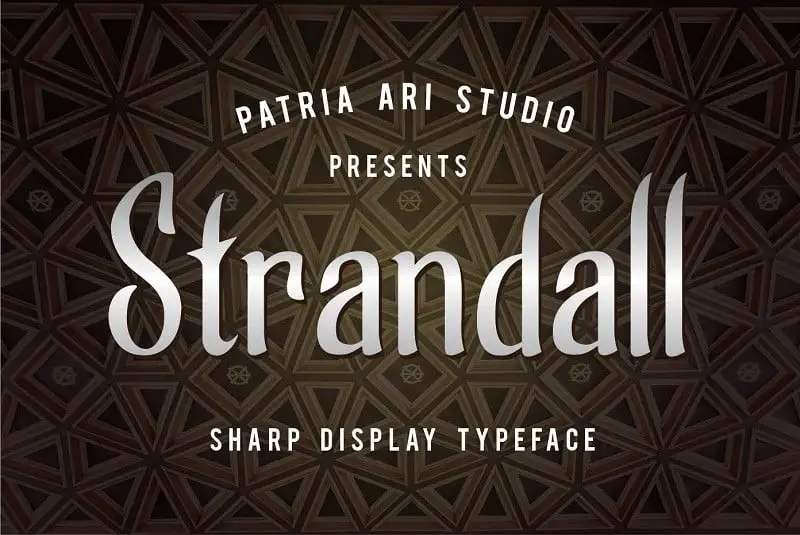
Strandall Display Font – Download Grátis
A “Strandall Display Font” é uma tipografia inspirada nas temáticas guerreiras, proposta para dar um toque poderoso aos seus projetos ou marcas. Com linhas aguçadas e linhas fortes, ela busca transmitir confiança e atrevimento. Este tipo de fonte foi criado com a intenção de reforçar sua marca ou projeto visual, adaptando-se perfeitamente para uso em logotipos, materiais de marketing ou qualquer outro material que precise de uma aparência imediata e poderosa. Seja você um estilista gráfico ou designer de identidade, esta fonte é a escolha ideal para criar elementos visuais impactantes e memoráveis. Inspirada nas lendas guerreiras da antiga guerra, ela carrega consigo os sentimentos de determinação e força que seus projetos merecem ter.